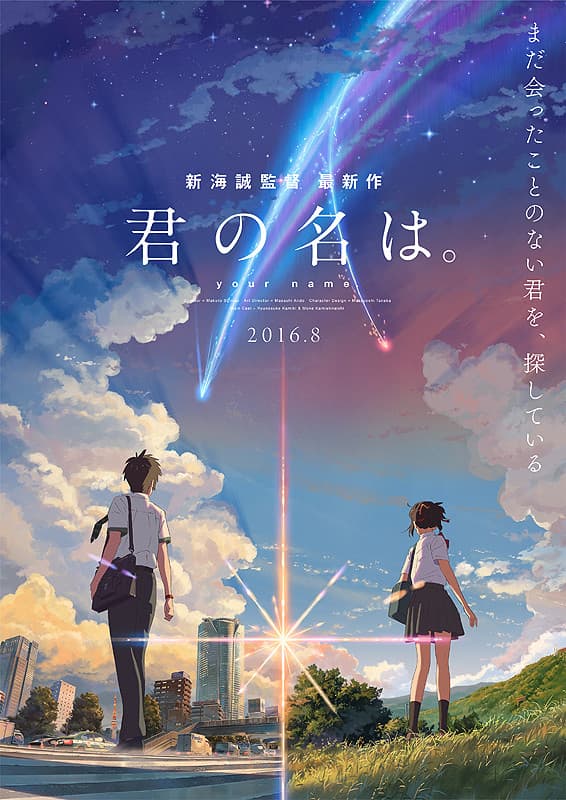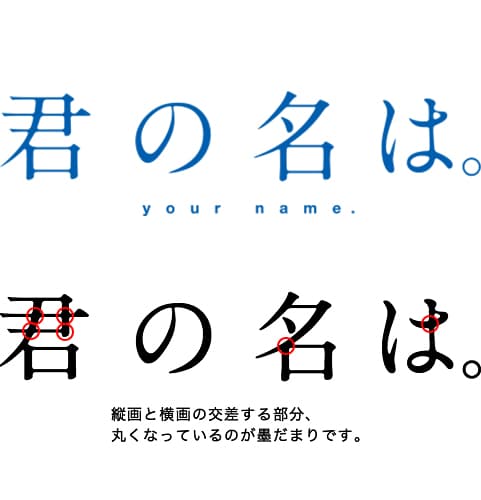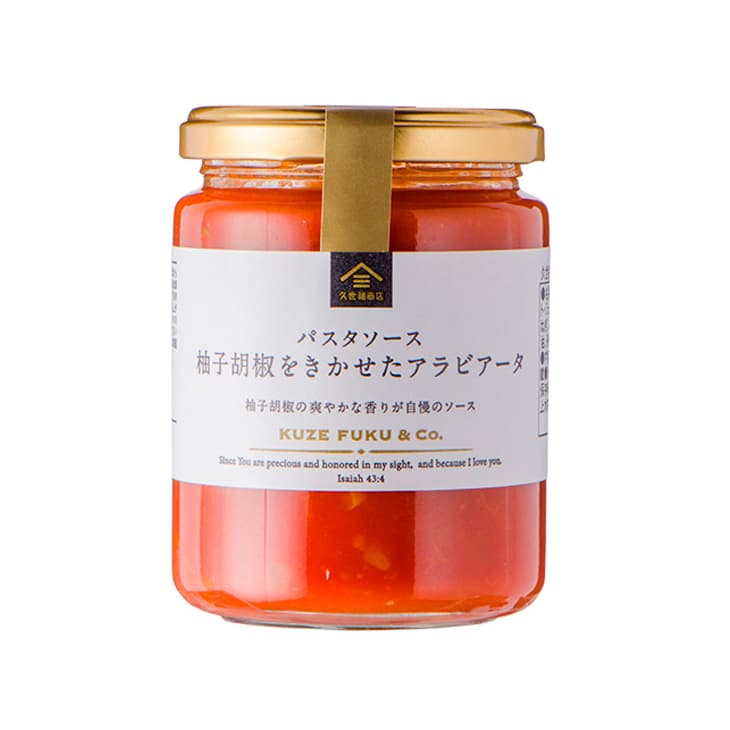
フォントから歴史と知識を学ぶこと
こんにちは。アシスタントデザイナーの川端です。 日々の生活のなかにあたり前に存在している文字ですが、何気なく見る看板やポスターにはさまざまなフォントが使われています。 その中で私が興味を持ったA1明朝について紹介したいと思います。
A1明朝を知ったきっかけは
A1明朝を知ったきっかけは、映画「君の名は。」です。
初めてタイトルを見た時は、誠実さや上品さ、これまで見てきた広告と印象が違うように感じ、映画の世界観が現れているように思いました。
調べてみると古くから親しまれてきたフォントであることを知り、新しい発見があったため今回ご紹介することに致しました。
ほかに探してみると身近にこんなものがあります。
久世福商店オリジナルレシピのパスタソース。「柚子胡椒をきかせたアラビアータ」のフォントにA1明朝が使われており、上品な雰囲気が出ていますね。
A1明朝の特徴
払いやカーブ、墨で書いた際に生じる「墨だまり」が再現されており、やわらかな印象と自然な温かみを感じるのが特徴です。このフォントにはなぜ墨だまりがあるのか、文字の歴史を振り返るとわかることがあります。
A1明朝の歴史を追う
日本語書体の歴史には大まかな流れがあります。
職人の手によって母型が作られていた時代から工業化に伴い、木版活字が金属活字へ。写真技術を使いフィルムに印字、パソコン一台で印刷ができる時代へと変化していきました。
まずその歴史について簡単に、木版活字、金属活字、写植機、DTPの順に追って簡単に説明していきたいと思います。
そもそも明朝体は、中国の宋体を元に開発された書体です。ヨーロッパ人が中国でキリスト教を広めるため、宋体活字の開発が続けられ製品化されたもので、職人の手によって彫刻が施された木材に墨を付け印字が行われていました。木版印刷は、中国から仏教や製紙技術とともに伝来したと言われ、その歴史は古く飛鳥時代に遡ります。
金属活字が日本へ
1896年長崎にウィリアム・ギャンブルを招き、日本へ金属活字が導入され、木版印刷から活版印刷へ。
金属活字に変わると、一度活字を作ってしまえばそれを何度も再利用して印刷物を作ることができるようになりました。その後、母型量産化のためベントン彫刻機が発明され、手書き文字をなぞるだけで母型を作成することが可能になり、生産性の向上に大きく貢献しました。しかし、まだ一つの文字ごとに母型を作る必要があったため文章を印字するのに時間がかかっていました。
発明したのは日本人
1924年に石井 茂吉と森沢 信夫により「写真植字機」が開発されます。写真植字は、文字を一字ずつ印画紙またはフィルムに焼き付け印字し、写真製版用の版下や焼き付け用のフィルム原板を作ることを言います。写真植字機を初めて実用化したのは、日本人だったんですね。
イギリス・アメリカでも研究・試作されていたのですが和文書体とは違い欧文書体は、一文字ごとのボディサイズが違うこともあり、それが開発を妨げる最大の要因だったようです。
手動植字最終系、使いやすさ、堅牢性など究極の万能型といえる手動写植機「MC-6型」
植字機ではこの文字盤を使い印字を行っていました。
当時、フォントサイズごとの母型を作成して文字を揃えるのに3日、印字に1日かかっていました。しかし、写真植字機が発明され一つの文字盤を使い印字することによって、作業時間の短縮、文字盤を変えることなくレンズを変えるだけでフォントサイズを変えることが可能になりました。
パーソナルコンピュータで印刷できる時代に
1987年、DTP(DeskTop Publishing)がアメリカから日本に上陸。
DTPという名所は「Adobe PageMaker」の販売開始にあたり、Aldus社の社長ポール・ブレイナードが1985年に提唱した言葉から来ています。パーソナルコンピュータの普及でDTPも一般化し、紙に書いた文字をスキャンしてデータがデジタル化されフォントとして使えるようになりました。
A1明朝の始まり
2005年に写真植字用明朝体「太明朝体A1」がパーソナルコンピュータ用のデジタルフォント「A1明朝」として復刻されました。写植元になったフォントからA1(13ポイント)がフォント名に使われています。写植機で印字を行うため、墨を使わないのに墨だまりが表現されていることを不思議に思った方もいるかと思います。
写真植字でも、活版印刷と似た現象が起こります。写植機は、カメラでフォルムに文字を印字します。その際、光源ランプが文字盤を通り、指定した文字サイズのレンズで印画紙に印字されるため、光を使用する以上現像された文字の輪郭は初めからぼけています。つまりわずかな「被り」がある状態。結果、縦画と横画の交差する部分は丸くなり、墨だまりのような滲みが表示されます。A1明朝では、この滲みを再現してやわらかな印象を表現しています。
気軽に使えるようになって嬉しい
歴史を追っていくと、それぞれのフォントに時代背景があり特徴が表現されていることがわかります。歴史の流れを理解することで、デザインの目的にあった書体を選びやすくなり、デザインで書体を使う際になぜこの書体にしたのか説得力が増します。
今回、書体に関する歴史を調べたことでなぜ墨だまりがあるのか、書体の意図が汲み取りやすくなりました。写植機がないと太明朝体A1が扱えなかった時代と比べて気軽にWebフォントとして使えるようになって嬉しいです。書体によって与える印象が変わって面白く思います。ポスターやWebサイトでのフォントの組み合わせと言ったような、相手に伝わりやすいデザインを作るためにも、タイポグラフィを楽しく学んでいきたいですね。